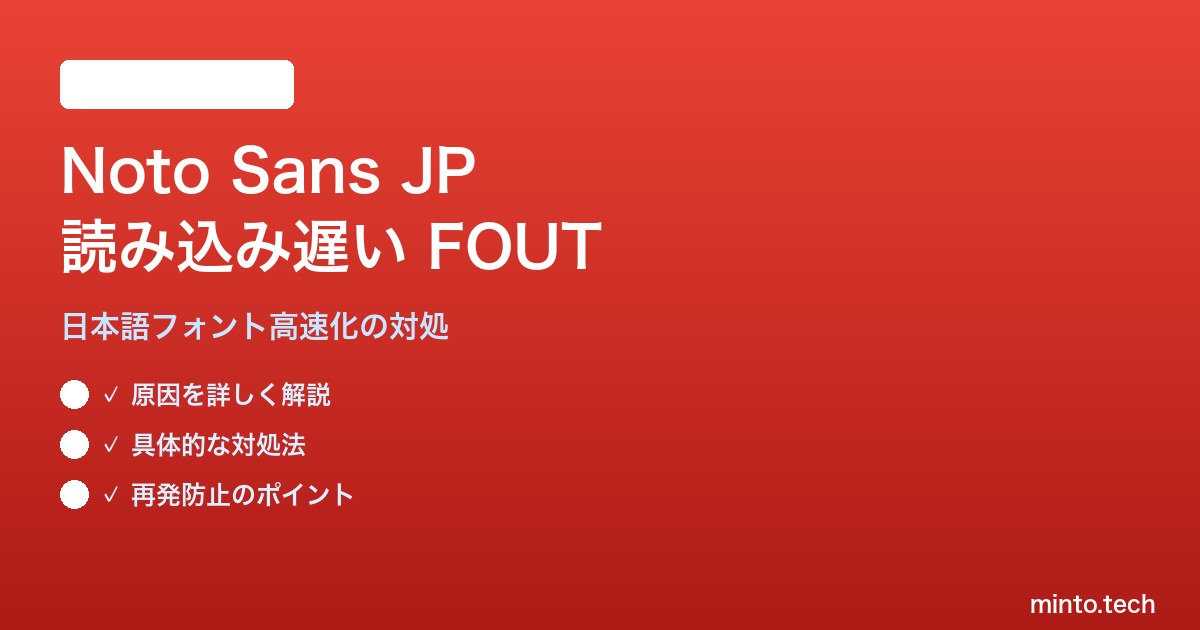
【2026年最新版】Google FontsのNoto Sans JPの読み込みが遅い・FOUTで表示が崩れる対処法【完全ガイド】
日本語 Web サイトで定番のフォントといえば Google Fonts が提供する「Noto Sans JP」です。デザインが端正で可読性が高く、商用利用もしやすいため、多くのコーポレートサイトやブログで採用されています。しかしこの Noto Sans JP には、ロード時間が長く First Contentful Paint(FCP)を遅らせる、フォント未読込時に標準フォントで一瞬表示されてからガクンと切り替わる「FOUT(Flash of Unstyled Text)」が起きる、という慢性的な悩みが付きまといます。
原因は明快で、日本語フォントは英字フォントと比べて漢字・ひらがな・カタカナを含むためファイルサイズが桁違いに大きいからです。Noto Sans JP の Regular ウェイト一つで標準的に 1.5 MB、Bold まで含めると 5 MB を超える容量になります。これを毎ページの初回訪問で全部ダウンロードさせていれば、回線が細いユーザーの離脱率が跳ね上がるのは当然です。
本記事では、Noto Sans JP の読み込み速度と FOUT を改善するための実践的なテクニックを段階的に紹介します。preload 属性、font-display: swap、サブセット化、self-host、CDN 比較といった、Web パフォーマンス改善の王道を網羅しているので、PageSpeed Insights のスコア改善や Core Web Vitals 対策を進めたい方にとって即効性のある内容になっています。
preload・font-display設定
この記事でわかること
• Noto Sans JP が遅い 5 つの根本原因
• preload と font-display の正しい使い分け
• サブセット化で 1.5MB を 200KB まで削減する方法
• Google Fonts と jsDelivr / unpkg の速度比較
• FOUT を完全に消すフォント切替テクニック
なぜ Noto Sans JP は遅いのか(基礎解説)
日本語フォントは収録文字数が膨大です。Noto Sans JP は JIS 第一・第二水準漢字、補助漢字、ハングル、絵文字なども含めて 17,000 字超を 1 ファイルに格納しています。Google Fonts は CSS 経由で複数のサブセット(unicode-range)に分割配信していますが、それでも漢字を含むサブセットだけで数百 KB あります。
さらに、Google Fonts のリクエストは fonts.googleapis.com から CSS を取得し、その中で fonts.gstatic.com に対してフォントファイルを別途リクエストするという 2 段階構造です。この間にブラウザは「フォントが届くまで文字を描画しない」という挙動(FOIT)か、「標準フォントで先に描画してから差し替える」挙動(FOUT)を取ります。前者はテキスト不可視時間が長くなり、後者はチラつきます。
2026 年現在、Google は HTTP/3(QUIC)配信を行っているため接続レイヤは高速化していますが、それでも 1 MB 級のフォントファイルを取りに行く事実は変わりません。改善のカギは「届いてから描画する」のではなく、「届いていない間どう振る舞うか」と「そもそも届けるサイズを減らす」の二軸で攻めることです。
原因切り分けチェック
1. Lighthouse の「Avoid enormous network payloads」で Noto Sans JP が表示されるか
2. Network タブで woff2 ファイルのサイズと時間を確認
3. Performance タブの Layout Shift にフォント切替が記録されているか
4. 初回訪問とリロード後でロード時間がどれだけ違うか
対処法1: font-display: swap を必ず指定する
Google Fonts の URL に display=swap パラメータを付けることで、フォントが読み込まれる前に標準フォントで先に描画されます。FCP が劇的に改善し、ユーザーは何かしらのテキストをすぐ目にできます。
<link href="https://fonts.googleapis.com/css2?family=Noto+Sans+JP:wght@400;700&display=swap" rel="stylesheet">
欠点は FOUT が発生しやすくなる点です。これは後述の preload と組み合わせて補います。
対処法2: preload で先取りロードする
HTML の head に preload を追加し、ブラウザに「この CSS / フォントを優先的に取れ」と指示します。
<link rel="preload" href="https://fonts.googleapis.com/css2?family=Noto+Sans+JP:wght@400;700&display=swap" as="style">
<link rel="preload" href="/fonts/NotoSansJP-Regular.woff2" as="font" type="font/woff2" crossorigin>
preload は強力ですが、入れすぎると逆に他のリソースを圧迫します。本当に最初に表示される範囲(above the fold)のフォントだけに絞るのがコツです。
サブセット化
対処法3: サブセット化で容量を 1/7 に削減
もっとも効果が大きい対処法です。サイトで実際に使う文字だけを切り出し、200KB 程度の小さい woff2 を生成します。
fonttools(Python)を使った例:
pyftsubset NotoSansJP-Regular.otf \
--unicodes="U+0020-007E,U+3000-30FF,U+4E00-9FFF" \
--flavor=woff2 \
--output-file=NotoSansJP-Regular-subset.woff2
上記は ASCII、ひらがな・カタカナ、CJK 統合漢字をカバーします。一般的な日本語サイトならこれで困りません。文字数を厳密に絞るなら、サイトテキストを --text-file=site-text.txt で指定する手もあります。
対処法4: self-host する
Google Fonts のサーバー応答時間や DNS 解決時間も遅延要因です。サブセット化した woff2 を自サイトに配置し、CSS から直接参照することで、外部リクエストを完全に排除できます。
@font-face {
font-family: 'Noto Sans JP';
src: url('/fonts/NotoSansJP-Regular-subset.woff2') format('woff2');
font-weight: 400;
font-style: normal;
font-display: swap;
}
HTTP/2 や HTTP/3 を有効にした自前サーバーや CloudFront・Cloudflare 経由なら、Google Fonts より高速になることも多いです。
対処法5: Variable Font 版を使う
Noto Sans JP には Variable Font 版(NotoSansJP-VF.woff2)があり、複数ウェイトを 1 ファイルで賄えます。Regular と Bold を別々にロードするより、結果的に総容量を削減できる場合があります。
CDN・配信方法の比較表
配信方法 初回ロード 2 回目以降 設定難易度 推奨度
Google Fonts(標準) 遅い 普通 低 小規模サイト
Google Fonts + display=swap FCP 早い 普通 低 標準的
jsDelivr CDN 普通 普通 低 代替
self-host(サブセットなし) 遅い 速い 中 非推奨
self-host(サブセット化) 非常に速い 非常に速い 中 強く推奨
Variable Font 版 self-host 速い 速い 中 多ウェイト使用時
FOUT を完全に消すテクニック
FOUT のチラつきが許容できない場合、CSS Font Loading API を使って「フォントが読み込み完了したらクラスを付ける」方式が有効です。
<style>
body { visibility: hidden; }
body.fonts-loaded { visibility: visible; }
</style>
<script>
document.fonts.ready.then(() => {
document.body.classList.add('fonts-loaded');
});
</script>
ただしこれは「フォントが届くまで何も見えない」状態を作るため、回線が細いユーザーには不評になりがちです。最低限のタイムアウト(1 秒)を設けて、超えたら強制表示する設計がベターです。
Q6. self-host のフォントを CDN に乗せたいです。
Cloudflare R2、AWS CloudFront、Vercel Edge Network いずれも woff2 配信に最適です。Cache-Control を 1 年(max-age=31536000, immutable)に設定すると効果が最大化します。
まとめ
Noto Sans JP は美しい反面、Web パフォーマンスの足を引っ張る代表格です。font-display: swap で FCP を即改善し、preload で重要フォントを先取りロード、サブセット化で容量を 1/7 に削減、最終的には self-host へ移行する、という 4 ステップで多くの問題は解決します。Core Web Vitals の合格ラインに届かないサイトは、まずフォント周りから手を入れてみてください。文字が届くまでの 0.5 秒の差が、ユーザーの第一印象を大きく左右します。